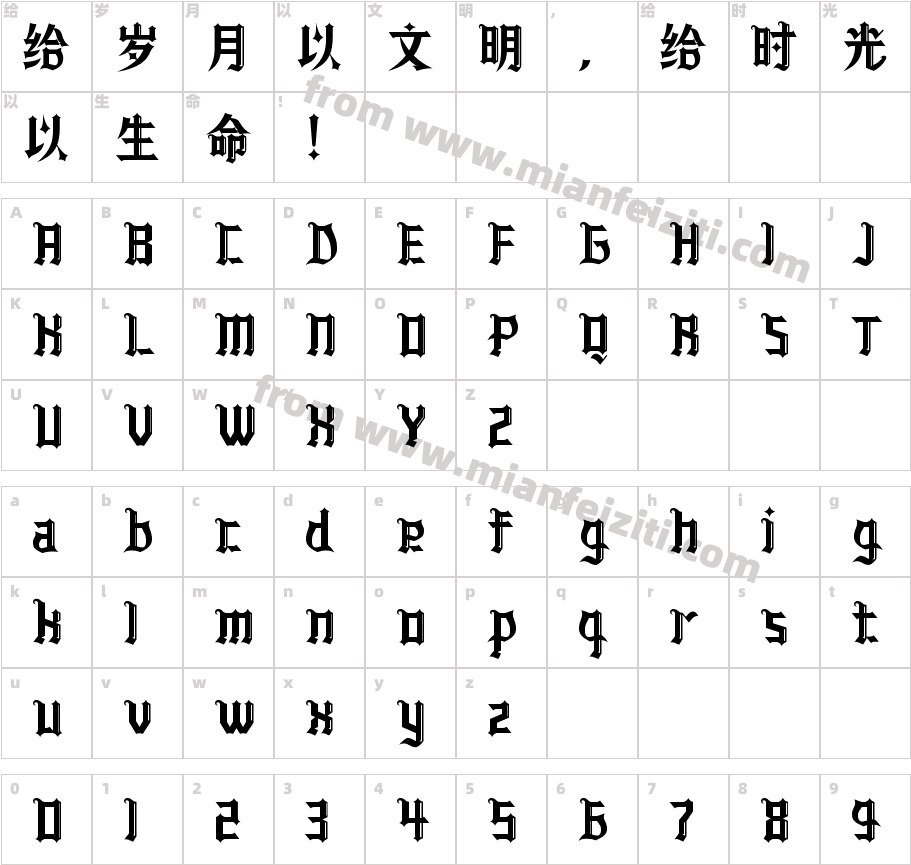
字语哥特体
字语哥特体的设计是提取了拉丁文哥特体的笔画元素,将古老的欧式手写风格融入在中文笔画之中。通过局部细线和留白的笔画勾勒,为字体增添清新不凡的质感。字语哥特体着眼让世界深入了解汉字文化的理念,将欧式的书写风格与汉字的优美形态相碰撞,力求促进汉字国际化发展的新路径,伴随中国文化输出,向世界传递多元的中华汉字之美。